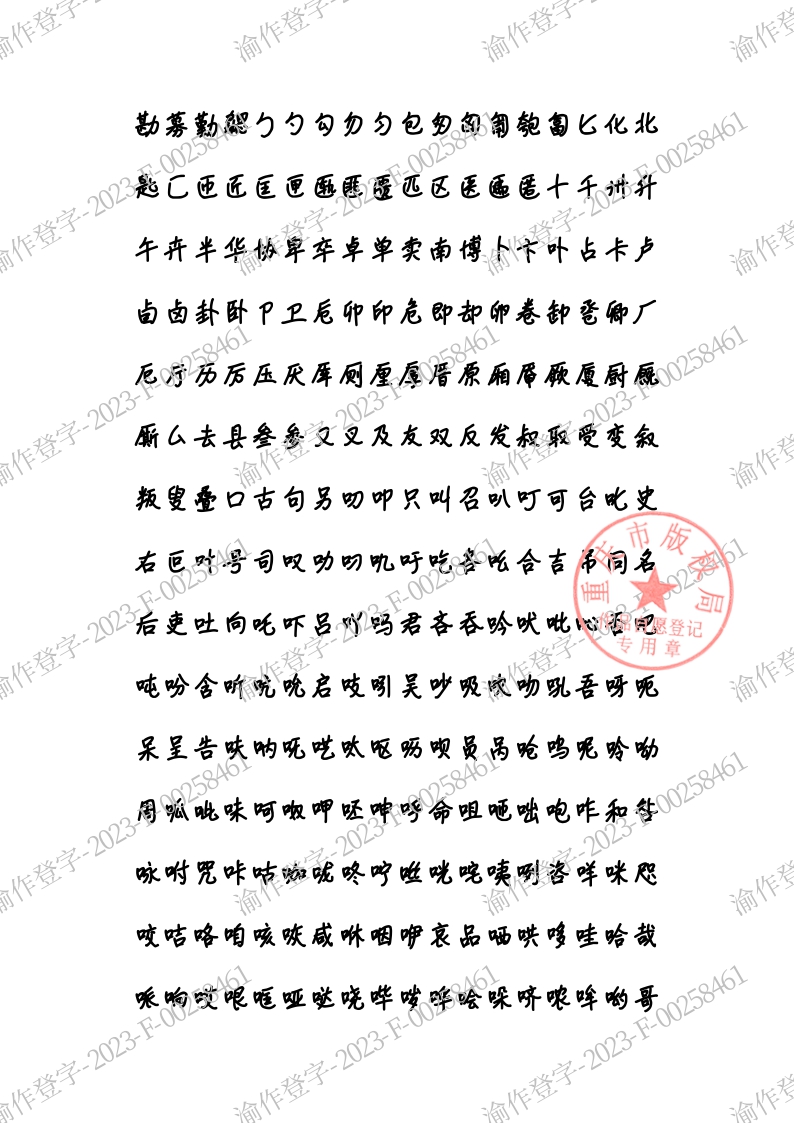
安景臣幼童圆体
儿童散学归来早,忙趁东风放纸鸢。
风格:美术字体
语系:中文-简体
字数:GB2312(6763字)
类型:圆体
安景臣幼童圆体
描述:该字体是安景臣模仿幼童书写效果而设计的一款天真烂漫、童趣十足的美术字体。广泛应用于幼儿园、中小学宣传及少儿读物、电视作品标题字幕、包装宣传等。具有字体醒目、容易辨识的优点。对于品牌的提升具有非常明显的效果。